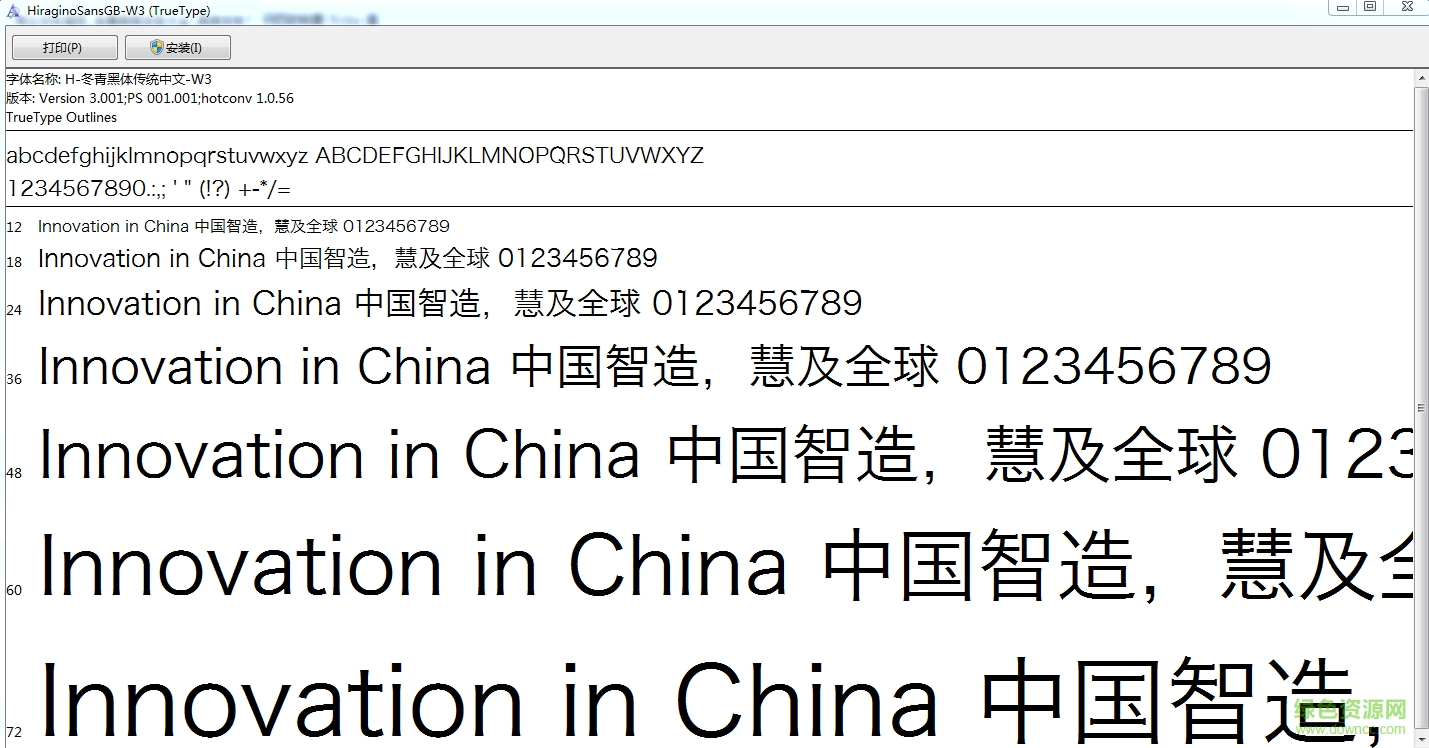
hiragino sans gb w3亮體
hiraginosansgb w3又名冬青黑體傳統(tǒng)中文字體,是一款應(yīng)用非常廣泛的簡體中文字體,結(jié)構(gòu)嚴謹,筆畫方正,適合一些正式場合使用!有興趣的朋友快來綠色資源網(wǎng)下載吧!
hiraginosansgbw3字體介紹
hiraginosansgbw3字體,非常厚實端正,能夠適用于平面廣告、書籍印刷等行業(yè),需要的用戶可免費下載收藏。